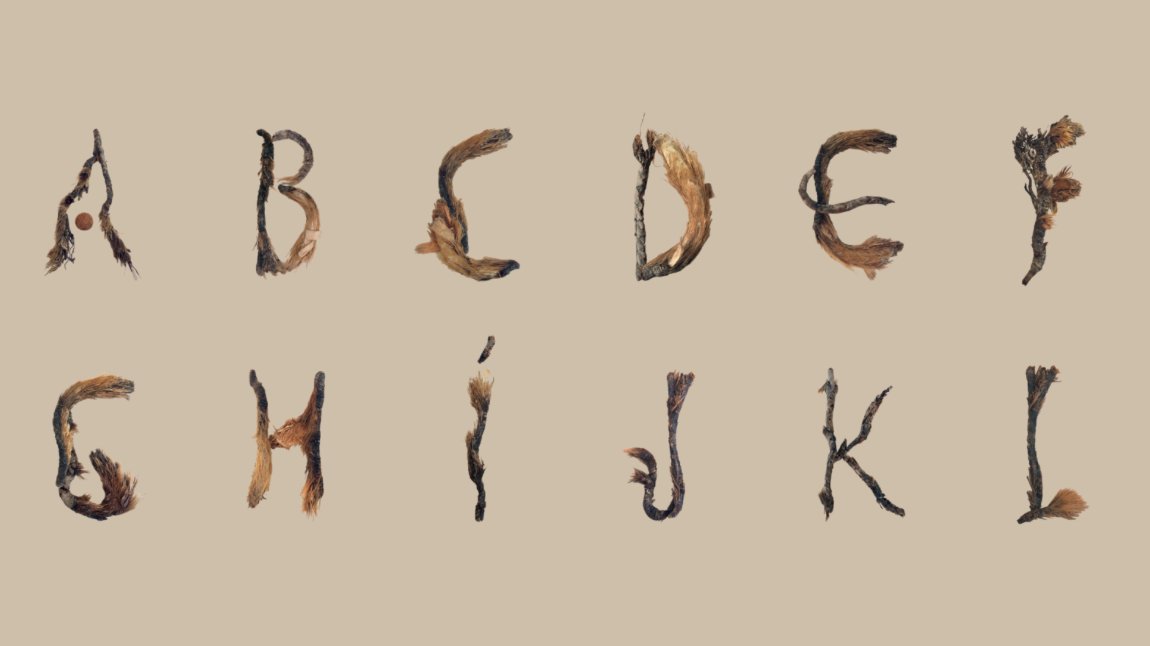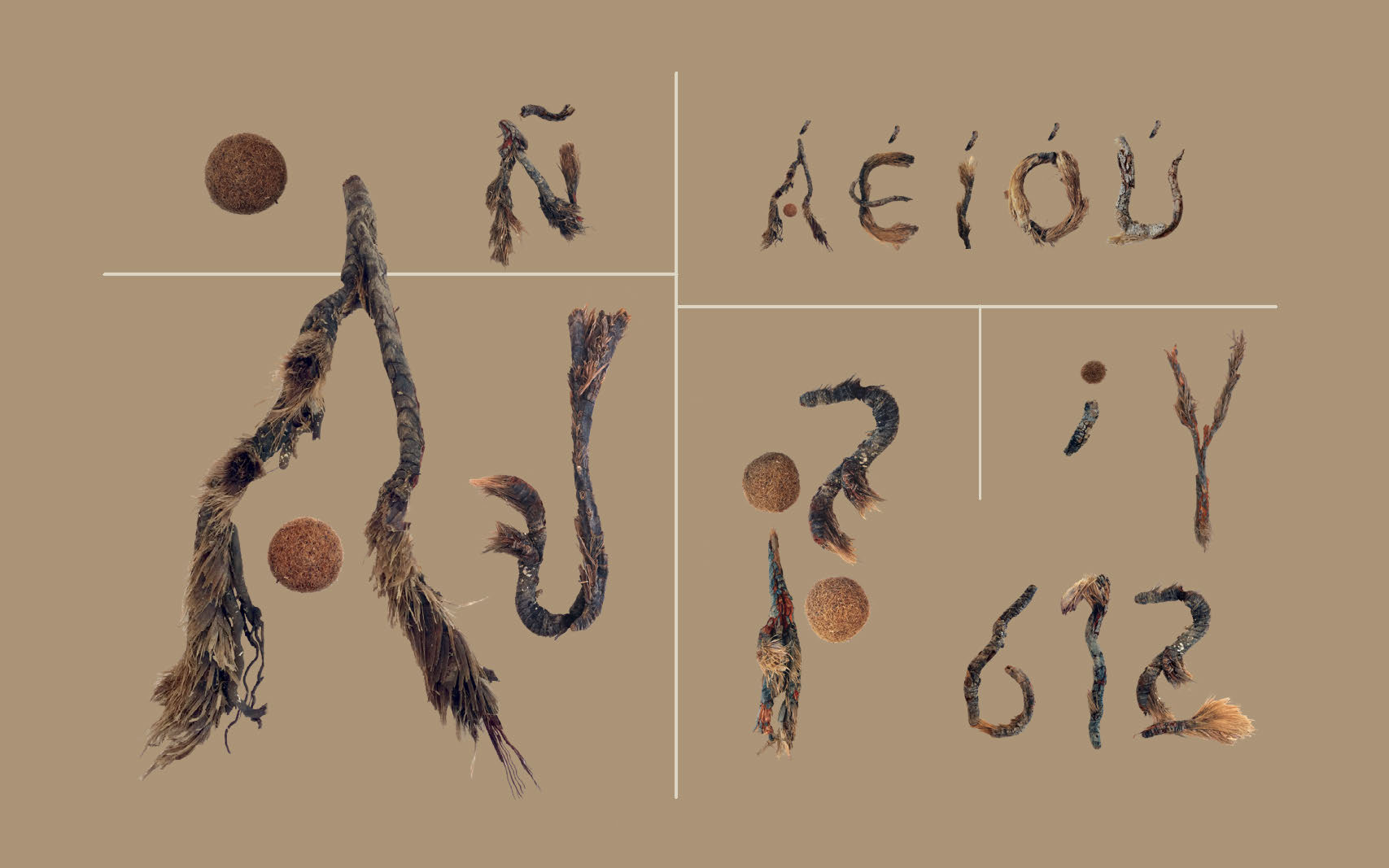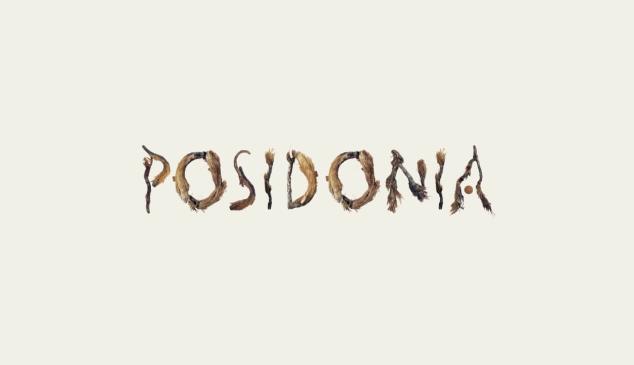
La Posidonia Oceánica es una planta marina característica del mar Mediterráneo, que forma extensas praderas verdes que liberan oxígeno a la atmósfera, proporcionan refugio a numerosas especies marinas, consolidan los fondos y frenan la erosión de la costa y de las playas.
La Posidonia Oceánica está disminuyendo de forma drástica
En definitiva, es una planta indispensable para la conservación del Mediterráneo.
Sin embargo, el número de Posidonias está disminuyendo alarmantemente por la contaminación del mar, la pesca de arrastre, la práctica irresponsable de deportes náuticos y la construcción de obras costeras, diques y otras barreras que modifican los procesos de sedimentación del mar.
Con el objetivo de visibilizar la importancia de esta planta para la salud del mar, y alarmar a la sociedad para que se haga responsable, el estudio de creatividad alicantino Posidonia Design ha diseñado una tipografía recogiendo posidonia seca de las playas y costas, y componiendo todas las letras y números con trozos de los tallos y de las hojas.
Una tipografía de uso libre y gratuito
El resultado de esta particular "recolecta" ha sido la creación de la primera tipografía del mundo basada en esta planta endémica del Mediterráneo, de uso totalmente libre y gratuito. “Queremos seguir disfrutando del Mediterráneo muchos años y que lo disfruten las generaciones futuras” comenta Luis Zaragoza, Cofundador de Posidonia Design.
“Y acordaros, cuando alguien os diga que la playa “está sucia y llena de algas”, ¡corregidle! No son algas, es una planta acuática que se llama Posidonia y su presencia indica que el mar está limpio, vivo y sano”, señala Marina Zaragoza, Cofundadora del estudio afincado en Alicante.